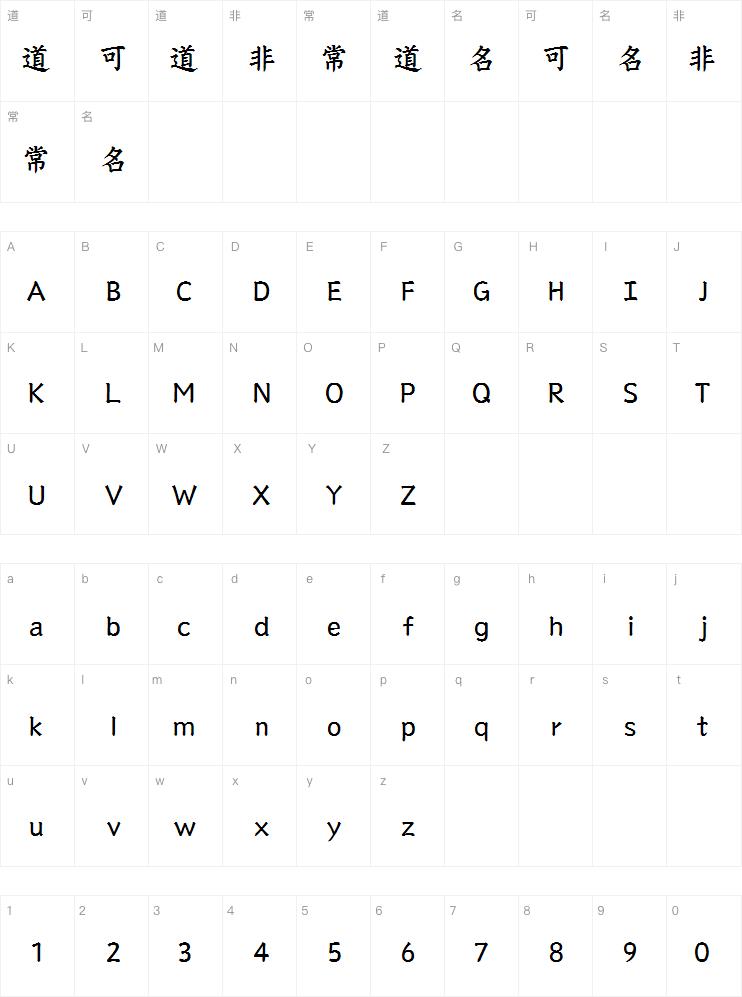
山海颜楷65w
山海颜楷65W,是一款全新的字体,是山海颜楷字体家族系列中的常规粗细款,编号65W,包含汉字9169个,符号200+个。该字体汲取中国唐代书法家颜真卿书法的颜体之特性,在汲取中创新,结合当代设计视觉环境,融入现代审美。字形方正,端庄严谨,古朴大方,起落顿笔有棱角。在饱有笔墨之意的同时,又刚柔并济。其结构方正茂密,笔画横轻竖重,笔力浑厚,挺拔开阔雄劲。三载创作,只为再现千年前大唐书法最高峰之风韵。